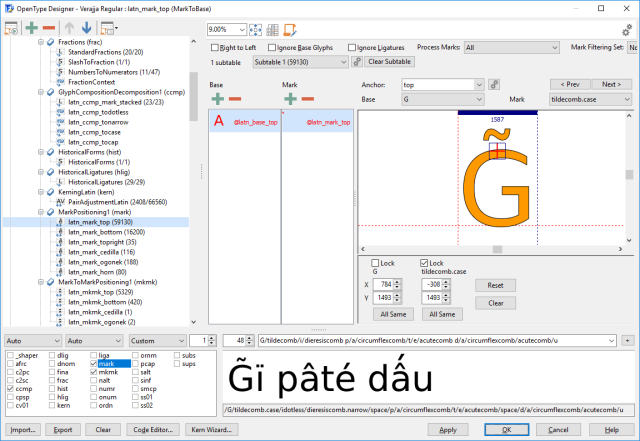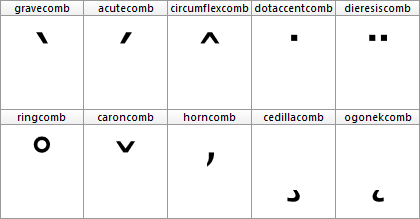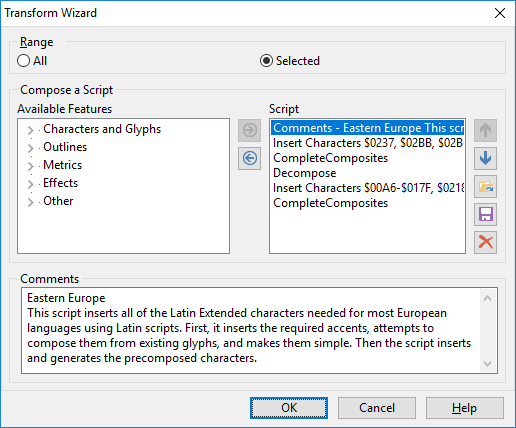
教程 拉丁语变音符号
No.20 Latin Accents
拉丁语 变音符号
本教程介绍如何让您与其他字体设计师都能用 FontCreator 为自己的字体添加拉丁文变音符号(重音)支持。
变音符号是用于创建复合字符的标记。这些变音符号主要出现在字母的上方或下方,但它们也可以在基础字符内,甚至在两个字母之间。变音符号在几种脚本中用于不同的原因。在拉丁文中,它们主要用于提供发音指导。其中一些标记也被称为重音符号(例如锐音、抑音、扬抑符和波浪号)。
基础字符具有前进宽度,因为它们定义了用于显示轮廓的水平空间。标记通常是无间距的,因为它们只属于基础字符而不改变组合所占用的空间。在从左到右的脚本(如拉丁文)中,这种无间距组合标记通常放置在左侧边距之前(因此字形具有负 LSB),以便与前一个字母组合。
变音符号示例
预组合字符
在设计字体的某个阶段,您可能想要添加预组合字符(例如 Ccedilla、aacute 和 edieresis)。预组合字符实际上是基础字符和一个或多个标记字符的组合,它也有自己的 Unicode 码点。从历史角度来看,它们被添加到 Unicode 中是为了确保该标准支持与已经包含此类预组合字符的其他编码标准之间的转换。
FontCreator(标准版和专业版)允许您通过插入字符和完整复合字形功能自动添加和生成此类字符。您还可以使用字形转换功能,这允许您快速添加对东欧、希腊扩展等的支持。显然,在您设计基础和标记字符后,它们效果最好。
字形转换功能
预组合字符不等于复合字形,但它们配合得很好。复合字形与字形轮廓在字体中的存储方式有关,因为复合字形由一个或多个其他字形的"软链接"组成。复合字形的好处是,当您修改基础或标记字形时,复合字形也会自动更新。
有些文本处理引擎(Illustrator?)会分解预组合字符,但似乎大多数文本处理引擎(Windows、Microsoft 应用程序、Firefox 等)对字符字符串执行 Unicode 规范化形式 C(规范组合)。这将把每个基础字符加上组合标记字符转换为规范预组合等效项(如果字体中可用)。例如,a + ◌̃ 变成 ã,但前提是字体中定义了 ã。
如果字体不支持预组合字符,它将只显示基础和标记,就像它们设计的那样。在这种情况下,标记可能完美地适合 e 和 o 上方,但标记在 w 上可能太靠右,在大写字符上可能太低。
如果您直接输入字体中不可用的预组合字符,则使用另一种字体来显示它,或者您将看到缺失字形(.notdef)。因此,包含预组合字符仍然很重要。
许多语言使用基础和标记组合,这些组合在 Unicode 中不可用作预组合字符(例如 g + ◌̃ → g̃ 和 G + ◌̃ → G̃,如巴拉圭瓜拉尼语中所用)。如前所述,将预组合字符包含到 Unicode 中或多或少是一种遗留机制,Unicode 联盟无意添加更多此类字符。幸运的是,人们可以将其输入为基础字符后跟组合标记字符。但如前所述,标记不会总是以这种方式正确定位。那么我们如何解决这个问题?
OpenType 定位功能
使用 OpenType 字体技术,有另一种方法通过使用 OpenType 定位功能将变音符号定位到基础字符。特定功能是标记到基础(mark)和标记到标记(mkmk)。mark 功能将标记字形相对于基础(或连字)字形定位。mkmk 功能将标记字形相对于另一个标记字形定位,因此您可以堆叠它们。这两个功能都使用附着点,也称为锚点。
在 FontCreator 中,我们可以通过 OpenType 设计器轻松添加 OpenType 功能代码。可以直观地完成,或通过编写功能代码完成。
编写此类代码很繁琐,但可能很有用。但如果您想要基于锚点的功能,则不需要它,因为 FontCreator 可以为您完成所有艰苦的工作!
OpenType 功能生成
向字体添加基于锚点的功能的最快方法是自动生成锚点,然后使用它们自动生成 OpenType 布局功能。您的字体需要组合标记。如果您的字体缺少它们,可以通过运行东欧转换脚本来添加它们。如果您的字体缺少锚点,只需选择所有字形并选择完整复合字形 → 基于锚点重新定位,以添加和定位几个基于拉丁文字符的锚点。
通常,对于放置在基础字形上方的变音符号,基础锚点在大写时垂直定位在 CapHeight,在小写字符时定位在 x-Height。常规标记的锚点垂直定位在 x-Height,但有一些例外,如 "k" 和 "t"。对于字形下方的变音符号(如 dotbelow 和 cedilla),锚点将设置在基线上。
不建议更改锚点的垂直位置,上下移动标记的轮廓要方便得多。在字形编辑窗口中移动锚点时按住 SHIFT 键会将移动限制为水平或垂直。或者可以使用锚点工具窗口设置其位置。
现在转到 OpenType 设计器,单击左上角的工具栏项,在此对话框中,选择基于锚点的定位,然后单击确定按钮。
OpenType 设计器 - 基于锚点的定位
OpenType 功能和查找现在已添加到您的字体中,如上所示。您可以输入预览文本来测试您的功能。您可以输入字母或斜杠后跟字母的字形名称。
越南语堆叠重音
如果字体包含组合的越南语声调标记,请确保这些字形使用正确的字形命名约定。例如,如果您创建了一个由 circumflexcomb 和 gravecomb 组成的字形,则将该字形命名为 circumflexcomb_gravecomb。
最大化变音符号
如果您想为大写和小写字母使用不同的标记,请添加带有 .case 后缀的标记变体(例如 gravecomb.case),并将其顶部锚点垂直定位在 CapHeight。.case 变音符号应该为大写字形正确定位,这通常远高于 CapHeight。
有些变音符号太宽,无法适应像 i 和 j 这样的窄字形,并且可能与相邻字形冲突。如果这导致文本可读性困难,请为这些例外添加带有 .narrow 后缀的标记变体。
具有小型大写字母和/或小型大写字母的字体可能会受益于额外的变体标记。对于小型大写字母,使用 .smcp;对于小型大写字母,使用 .pcap。如果您想为小型大写字母和小型大写字母都使用标记,则只添加带有 .cap 后缀的标记。
如果您坚持上述命名约定,OpenType 功能生成器就知道如何包含基于锚点定位的正确功能和查找。
添加变体标记后,请务必对受影响的复合字形重新应用完整复合字形 → 基于锚点重新定位。
自动重新定位字形成员
默认情况下,对锚点所做的更改不会传播到复合字形,因此您也需要对这些更改重新应用完整复合字形 → 基于锚点。这可能很繁琐,您甚至可能在每次更改后忘记手动执行此操作。为了确保您的复合字形始终与锚点同步,您可以从上下文菜单中将复合字形设置为自动附加。